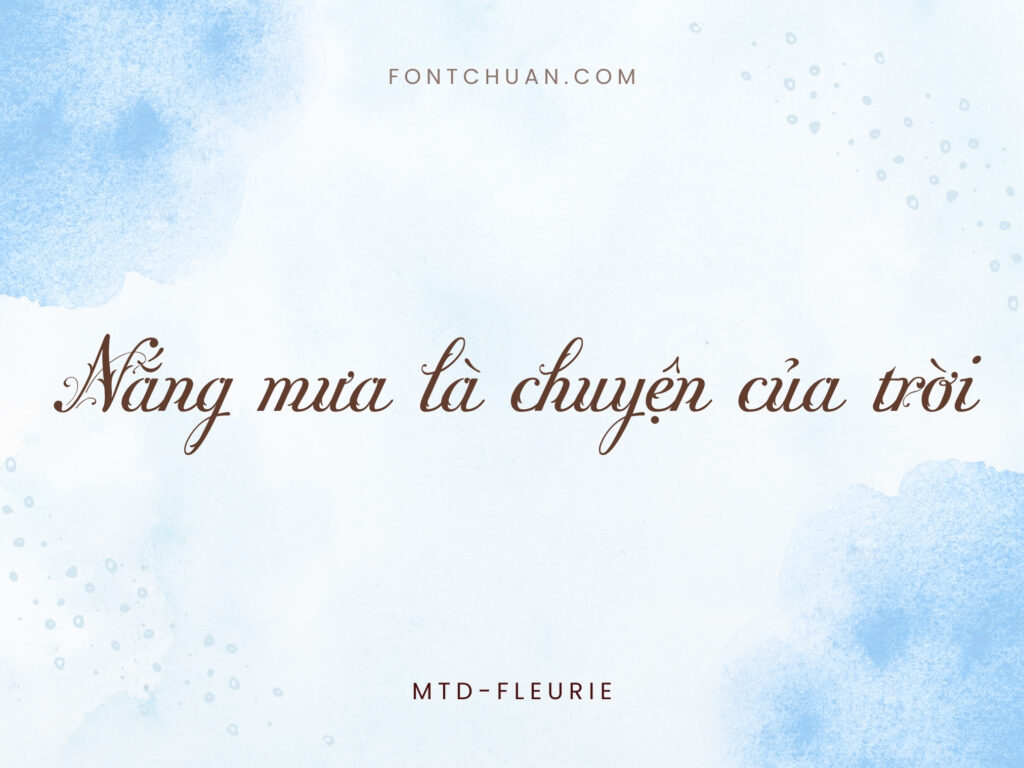
Font MTD Fleurie Việt Hóa
Font MTD Fleurie là một phông chữ script trang trí, mang phong cách thanh lịch và sáng tạo. Đây là một dạng Font chữ viết tay mềm mại, được Việt hóa bởi Mộc Hạ, hỗ trợ tiếng Việt và hơn 90 ngôn ngữ khác, giúp mở rộng khả năng ứng dụng trong các thiết kế đa ngôn ngữ. MTD Fleurie được cộng đồng thiết kế đánh giá cao và ứng dụng trong nhiều dự án sáng tạo, đáp ứng nhu cầu đa dạng của người dùng. Khi kết hợp cùng Font chữ công nghệ, Fleurie có thể tạo nên sự cân bằng độc đáo giữa nét thủ công tinh tế và phong cách hiện đại, phù hợp cho cả thiết kế sáng tạo lẫn chuyên nghiệp.
MTD Fleurie nổi bật với các đường nét mềm mại, uyển chuyển và mang đến cảm giác tự nhiên và thân thiện. Font rất phù hợp cho các thiết kế logo, thương hiệu cá nhân, thiệp mời, tiêu đề, bao bì sản phẩm và các ấn phẩm đòi hỏi sự tinh tế và cá nhân hóa. Các ngành nghề phù hợp bao gồm quảng cáo, giáo dục, công nghệ, thiệp cưới và ảnh cưới. Font này cũng lý tưởng cho các sự kiện như Tết, Giáng sinh, Valentine và các lễ hội khác.